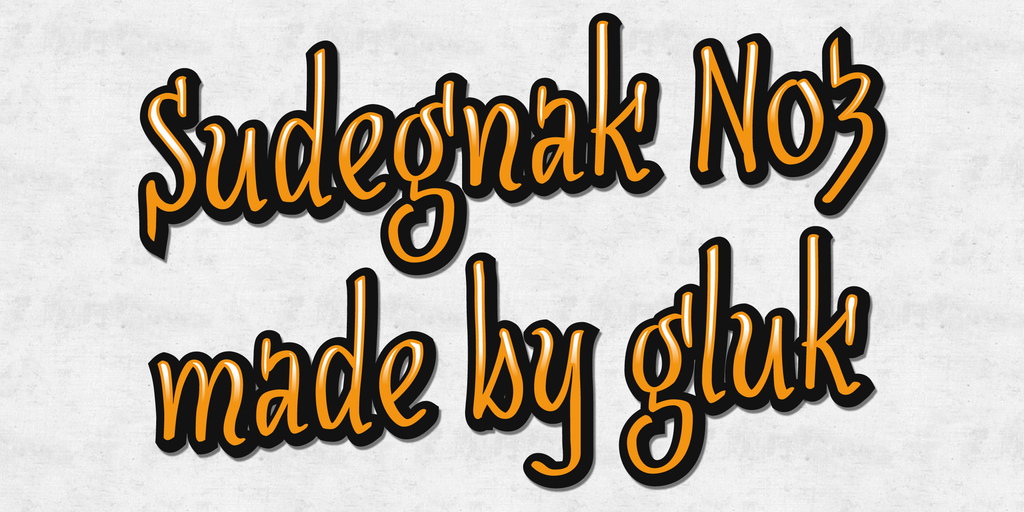
SudegnakNo3 Font Family
SudegnakNo3 é uma fonte do tipo playful criada pelo designer Hamilton que traz três camadas para oferecer variabilidade interessante. Com características escritas a mão e cheias de desenho cartunístico, esta fonte é ideal para textos coloridos e divertidos. SudegnakNo3 (incluindo as variações No3a e No3c) apresenta alternativas contextualizadas que oferecem uma diversidade interessante de opções de letras. Para quem está buscando adicionar um toque único e descontraído aos seus projetos gráficos, SudegnakNo3 é a escolha perfeita. Seja para nomes de negócios criativos, banners divertidos ou qualquer outro tipo de material que você queira destacar com uma escrita diferente, esta fonte trará um toque único e divertido ao seu projeto. Sua simplicidade e versatilidade a tornam um recurso indispensável para designers, gráficos e criativos em geral.